丸シール15mm 棒人間フォント
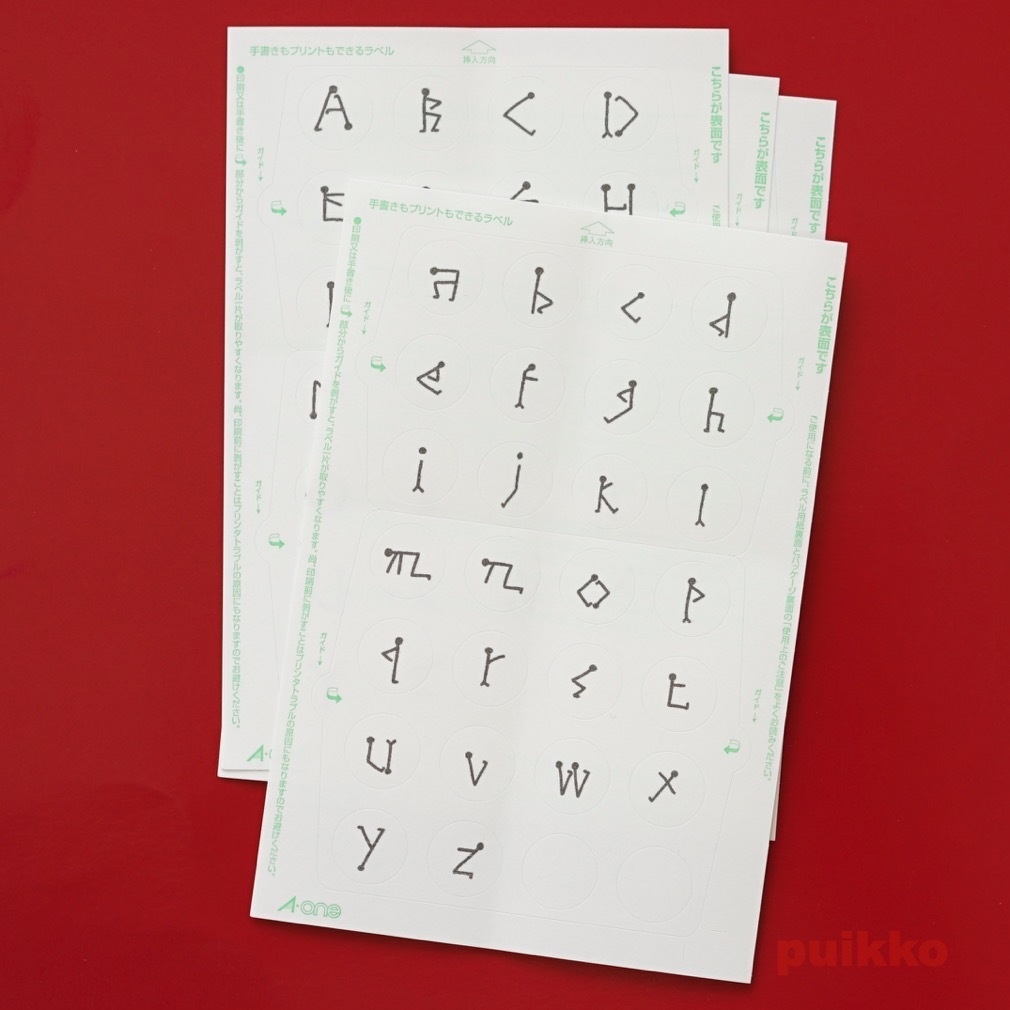
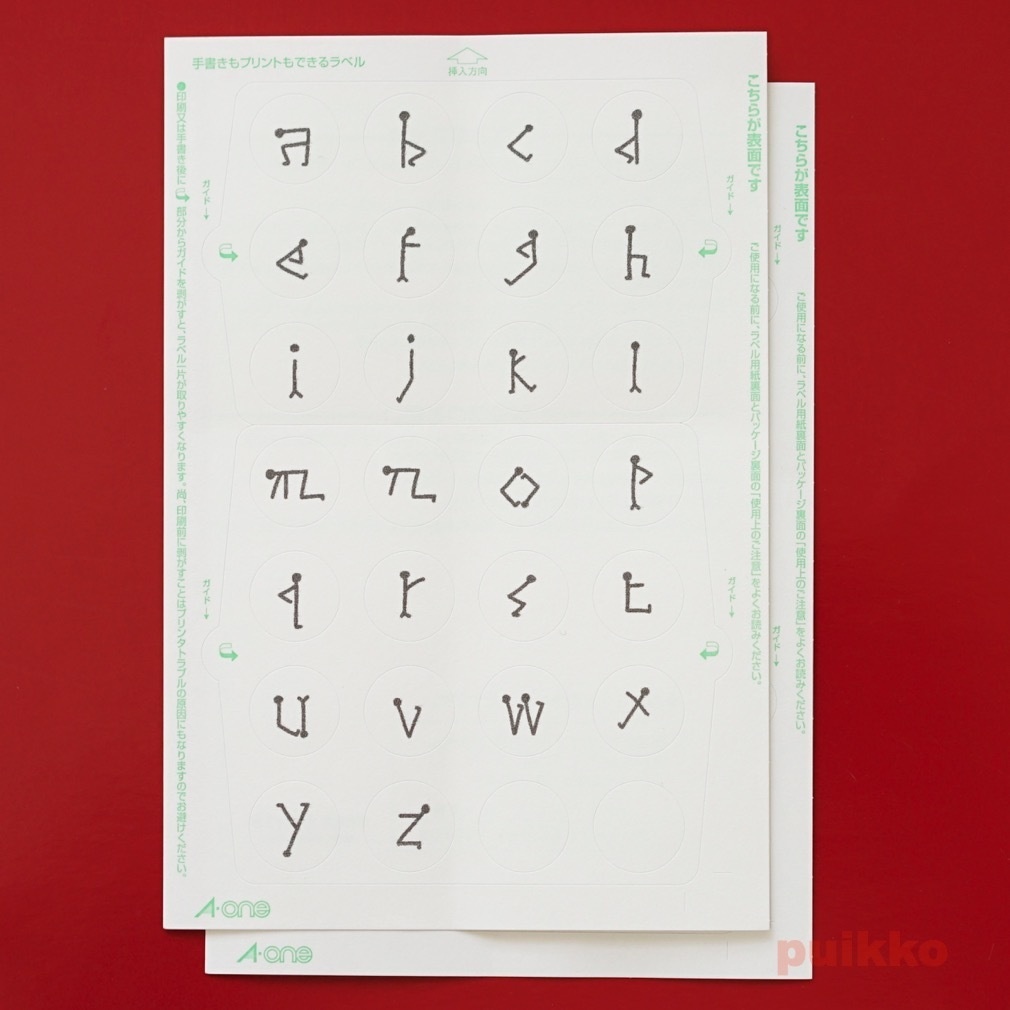
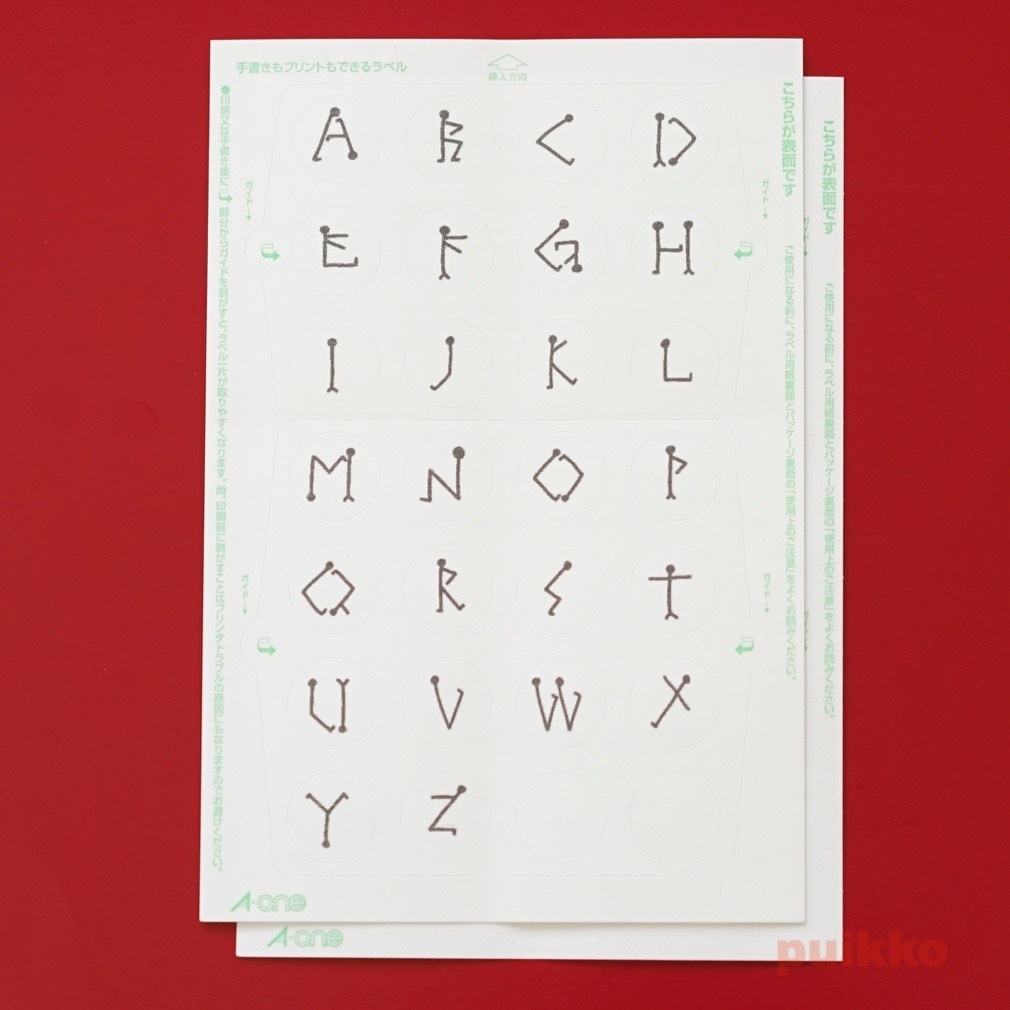
棒人間フォントをラベルシール(直径15mmの丸シール)に印刷しました。 そのまま貼って装飾にする、手帳に貼る、手紙の封緘にするなど、用途はさまざま。 puikkoオリジナルの英文字フォント「棒人間フォント」。なるべくアルファベットの形にあわせるように棒人間が逆立ちしたり、2体でひとつの文字を表したりと工夫をこらしています。 大文字A〜Z、小文字a〜zの計52種、各2片入り。 全104片、空白8片(28片×4シート) シールのサイズ 直径15mm 【素材】 ラベルシール マット紙・ホワイト 【サイズ】 幅100×高さ148mm(はがきサイズ)×4枚 【購入の際の注意点】 市販のインクジェットプリンタを使って印刷しているので、図柄がシールの円の中心からずれていることがあります。あらかじめご了承ください。 防水されていませんので紙濡れにご注意ください。